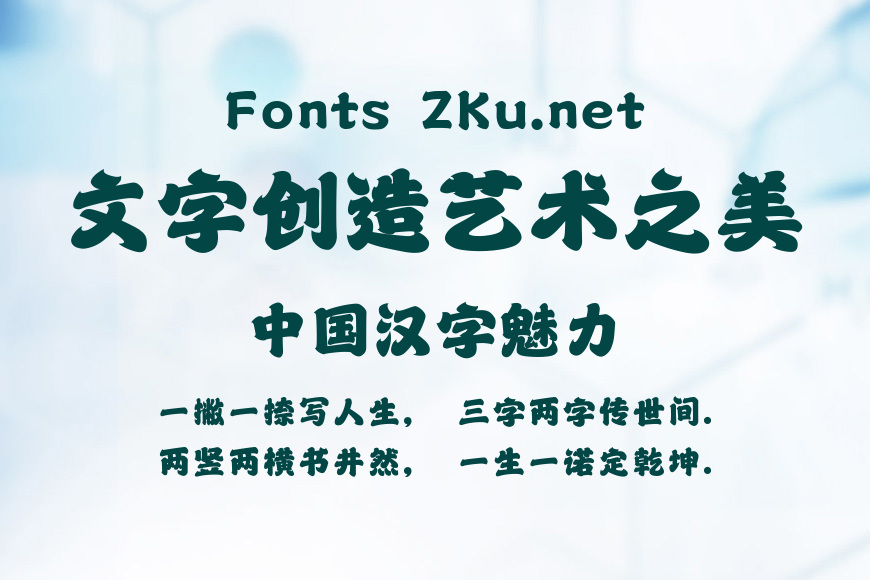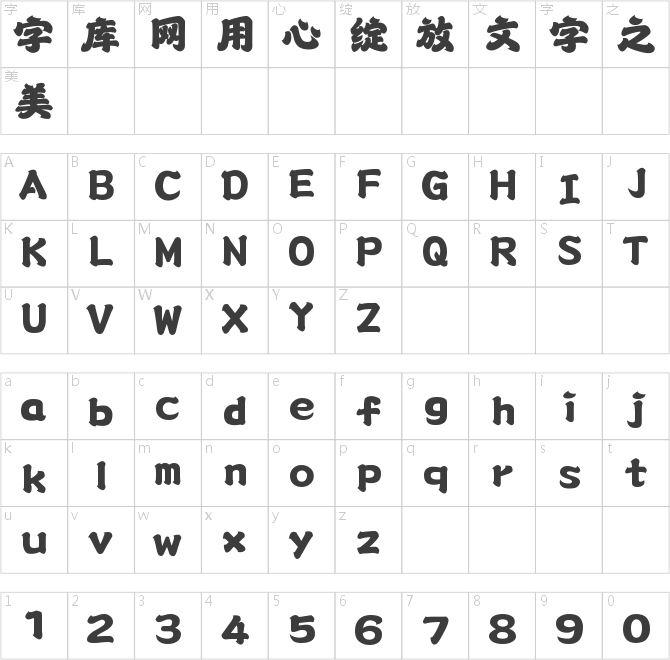
山海怒潮榜书
山海怒潮榜书介绍
山海怒潮榜书,是一款擘窠大字榜书字体。包含简体汉字6763个。该字体雄健有力,霸气外露,在粗细的纵横间,拥有非常规的张力特性。该字体的笔画充满力量感,组合搭配极富强烈的节奏感,融入楷书特点,使字体的视觉效果有力、宽厚、方正,充满了稳重感和设计感。笔画与字形间透露着榜书的古雅和刚劲的特点,在浑厚的同时而又极富张力,桀骜不驯的特性,霸气外露。